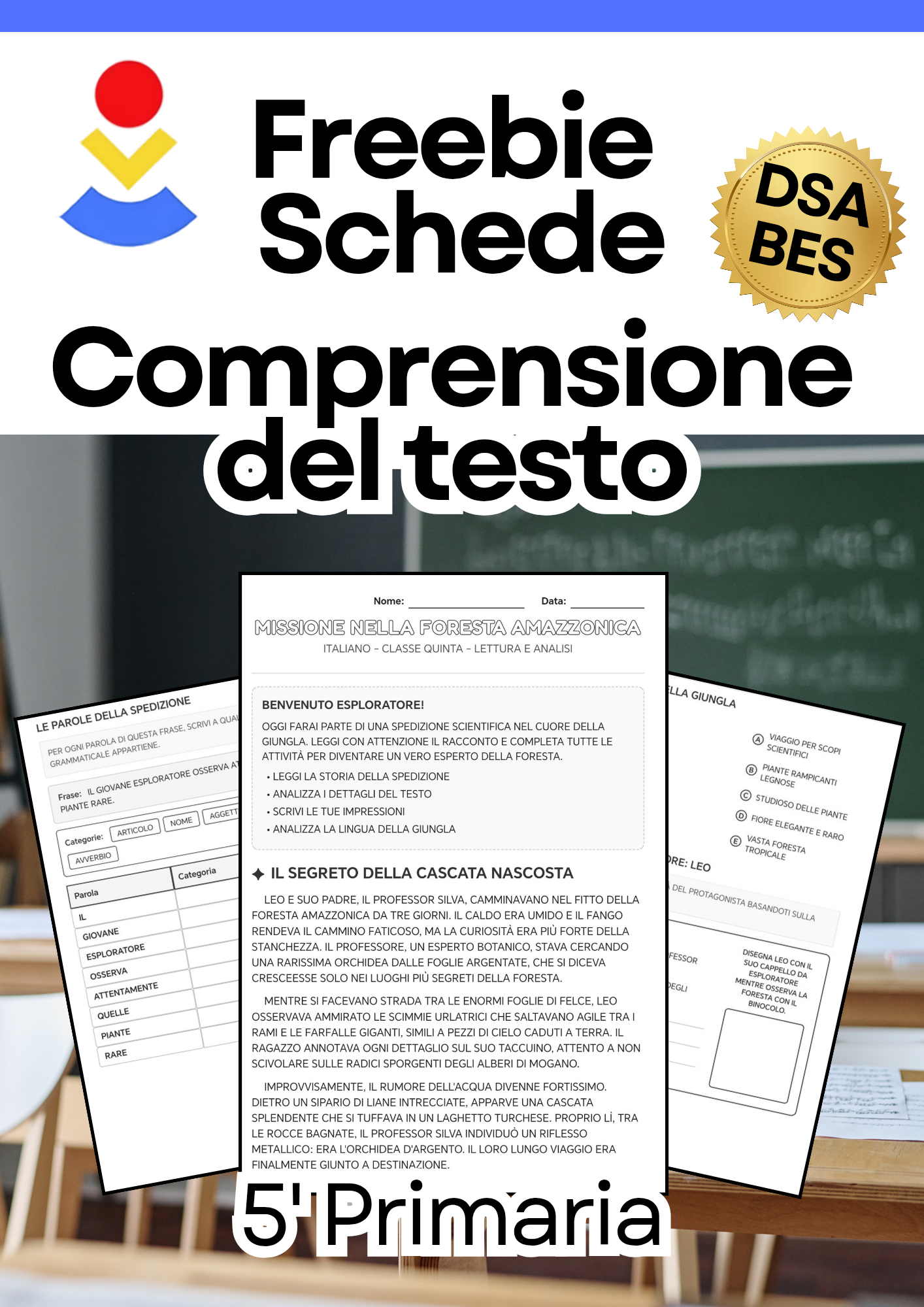
Porta l'avventura in classe con questa serie di percorsi interdisciplinari pensati per la classe 5ª della scuola primaria. Il materiale è progettato per coinvolgere gli alunni attraverso racconti immersivi, stimolando la comprensione del testo, l'analisi grammaticale e il pensiero critico.
Il bundle offre una soluzione inclusiva per gestire la variabilità dei ritmi di apprendimento all'interno della stessa classe. Ogni avventura è proposta in due versioni distinte:
​Versione Base: Ideale per lo svolgimento standard delle attività, con una struttura chiara e una grafica coinvolgente.
​Versione Alta Leggibilità: Progettata per favorire l'accessibilità e l'inclusione. Utilizza il font EasyReading, una spaziatura ottimizzata e il testo interamente in maiuscolo, rendendo il contenuto accessibile anche ad alunni con DSA o difficoltà di lettura.
​Racconti tematici: Dalle profondità della foresta amazzonica ai ghiacci del Polo Nord, fino ai misteri archeologici.
​Attività strutturate: Esercizi di comprensione, analisi grammaticale (articoli, nomi, aggettivi, verbi, avverbi), riflessione critica ed esercizi di causa-effetto.
​Approccio UDL: Materiali strutturati con una chiara gerarchia visiva per facilitare l'autonomia dello studente.
Bundle Avventure Esplorative: Classe 5ª - Versione Standard e Alta Leggibilità (Font EasyReading)